오늘은 웹(Web) 개발에 유용하게 사용할 수 있는 Font Awesome에 대해서 소개해드리려고 합니다.
웹페이지를 이쁘게 꾸미려면 적재적소에 아이콘들을 넣어야 하는 경우들이 있습니다. 아이콘이란 어떤 기능을 직관적으로 보여주는 디자인 요소를 의미합니다. 물론 아이콘을 이미지의 형태로 삽입하는 것도 가능하지만, 아이콘을 문자처럼 사용할 수 있다면 편리한 점이 많습니다. 아이콘을 문자처럼 쓸 수 있게 해주는 것이 바로 Font Awesome에서 제공하는 서비스입니다.
예를 들어, 북마크 기능을 나타내기 위한 아이콘을 사용하려면, Font Awesome 검색창에 북마크를 입력한 후 나오는 것 중에 무료인 것을 사용할 수 있습니다.
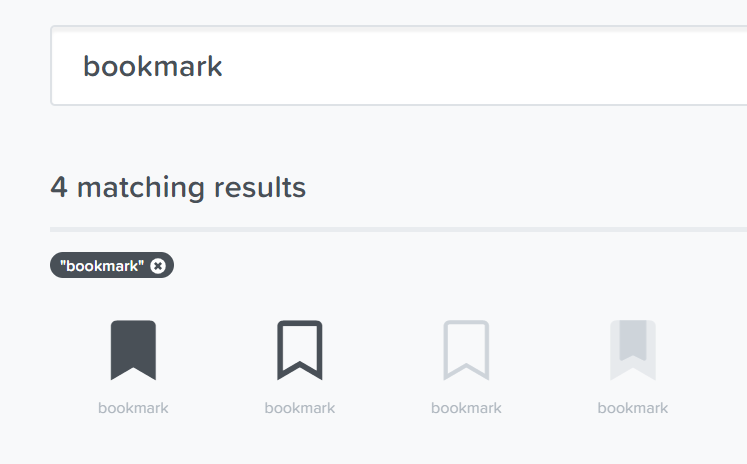
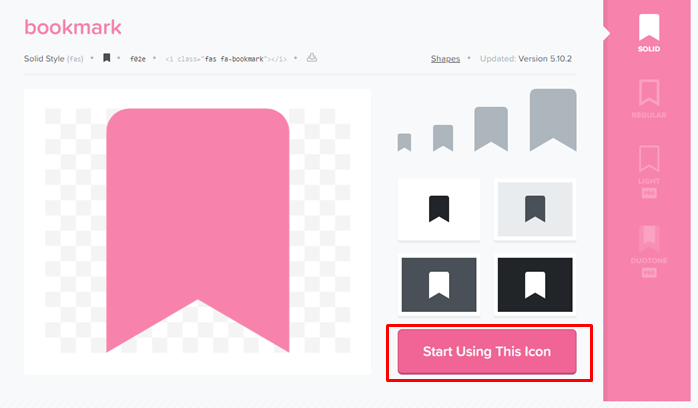
북마크 아이콘이 잘 삽입된 것을 확인할 수 있습니다. 그러면 이제 아이콘을 웹폰트 형식으로 사용할 때의 장점을 보여드리겠습니다. 먼저 아이콘의 크기를 바꿔보겠습니다. 또한 색상도 바꿔보겠습니다. 크기를 바꿀 때는 CSS의 font-size 속성을 사용하면 되고, 색상을 바꿀 때는 color 속성을 다루면 됩니다. 모두 문자를 꾸며줄 때 쓰는 CSS 속성들인데 동일하게 사용할 수 있습니다.
보시다시피 글자를 다루듯이 아이콘을 다룰 수 있습니다.
마지막으로 북마크를 실제 사용될만한 위치에 놓아 보겠습니다. CSS의 float 속성을 이용해서 북마크를 페이지의 오른쪽에 위치하도록 하겠습니다. 또한 margin-right 속성을 이용해서 북마크가 너무 오른쪽에 붙지 않게 하겠습니다.
꽤 그럴 듯하죠? e-book 리더기 같죠? ㅎㅎ
오늘 보여드린 것처럼 font awesome을 활용하면, 아이콘을 문자를 다루듯이 쉽게 다룰 수 있습니다. 이름만 기억해두셨다가 쓰실 일이 생기면 써보시길 바랍니다.